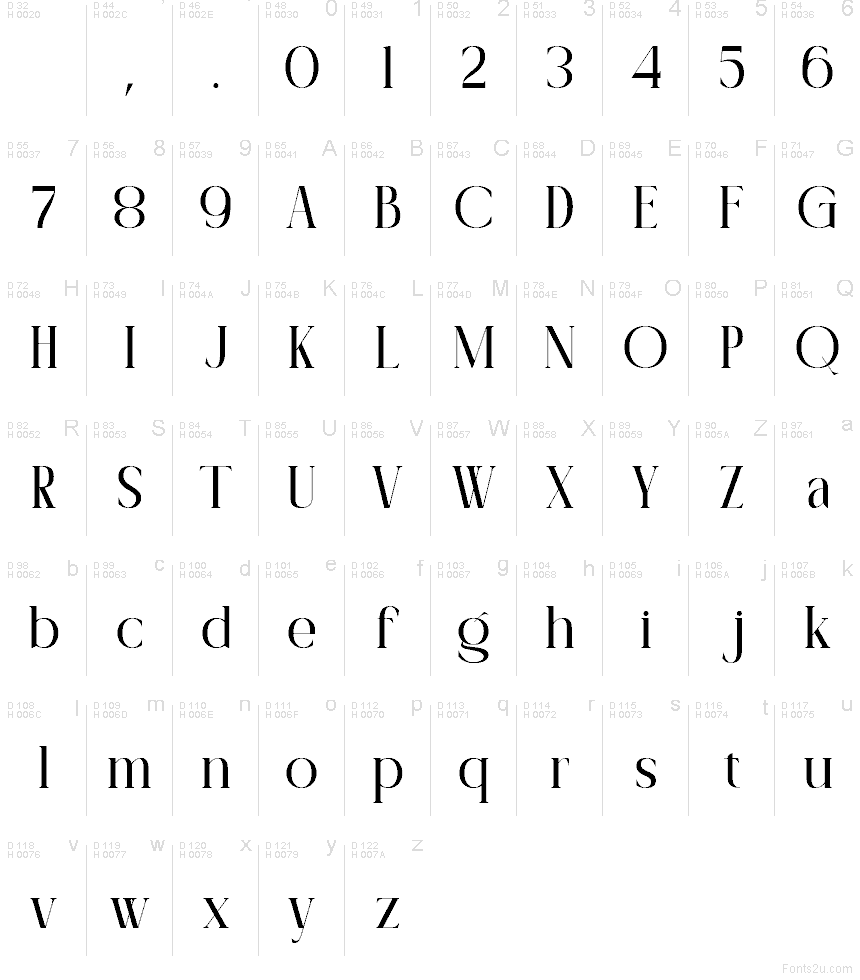
Calivorne Regular
Calivorne od Muksal Creative je bezplatné, vysoko kontrastné písmo, definované výrazným vertikálnym dôrazom a jemne zúženými krivkami, ktoré dodávajú písmenám elegantnú, redakčnú siluetu. Ostré prechody od širokých ťahov k vlasovým spojeniam vytvárajú vycibrený rytmus, ktorý pôsobí skôr ako módne titulky než ako bežný knižný font.
Tento charakter sa výborne hodí na hlavičky časopisov, butikové balenia, svadobné tlačoviny, branding parfumov či menu luxusných podnikov. V krátkych riadkoch Calivorne skvele zvýrazní logá a grafiku na sociálne siete, pretože úzke spoje a rozmáchle krivky vnášajú do textu rafinovaný pohyb bez toho, aby pôsobil príliš zdobene.